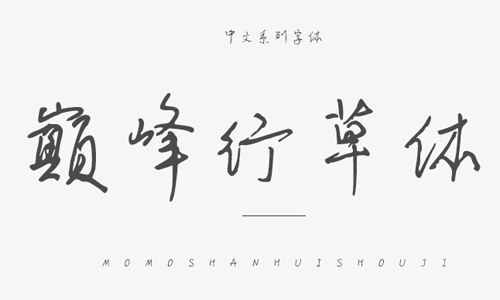
巔峰行草體字體是一款能夠讓你在各類編輯中直接使用行草效果的書法字體,該字體在潦草中帶有十分舒適的視覺效果,讓你感覺到中華行楷的博大精深,各類獨特的字體風(fēng)格都無法與它相提并論,本字庫是在國家標(biāo)準(zhǔn)簡體字庫GB2312所包含6763漢字的基礎(chǔ)上,又增加了近200常用字,已經(jīng)覆蓋了大陸99.75%的漢字使用頻率,足以滿足日常需求,歡迎需要此字體的朋友前來下載使用。